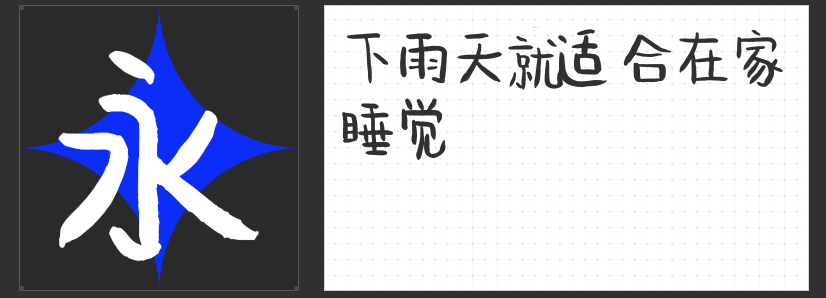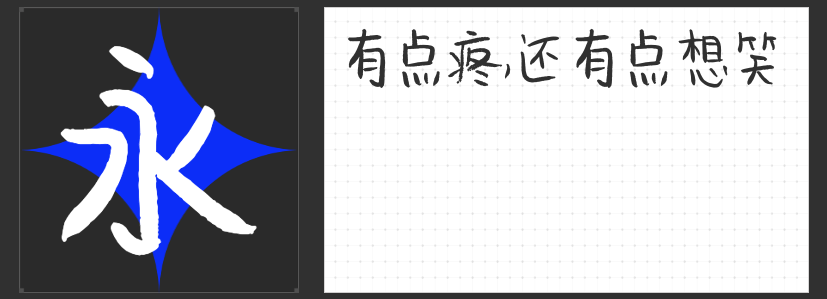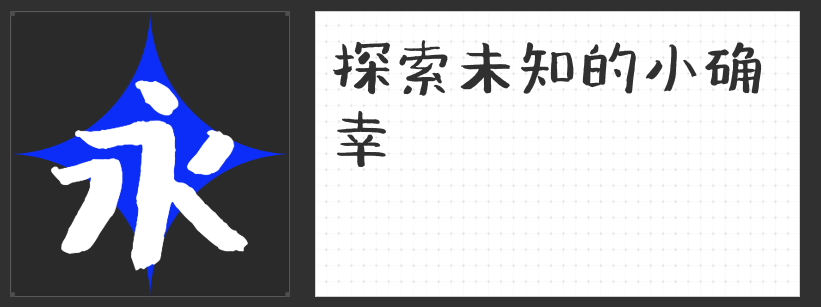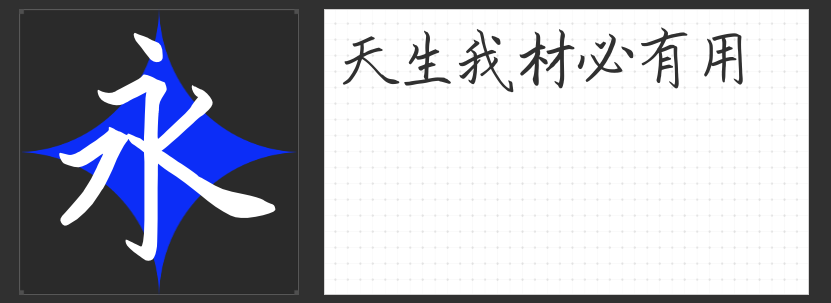
笔墨传情,手写温度——四款风格化字库字体解锁设计新维度
在数字化浪潮中,手写字体的独特韵味始终无法被替代。它承载着书写者的情感温度,传递着文字之外的视觉语言。本文精选四款风格各异的手写字库字体,它们既遵循传统书写规范,又融入现代审美巧思,为设计注入鲜活生命力。
一、安景臣标准楷书
这款字体以传统欧体为根基,却在细节处突破常规:撇捺笔画适度伸展,打破楷书常见的拘谨感,形成舒展而不失力度的视觉节奏。其字形结构严格遵循汉字书写规范,每一笔都经得起推敲,既可作为书法字帖的出版范本,亦能胜任广告标题、包装设计等商业场景。在需要传递权威感与文化底蕴的设计中,标准楷书以“正大气象”的姿态,成为平衡专业性与艺术性的理想选择。
二、高手北半川丰收体
以“顿感”为设计核心,丰收体的笔画末端自带圆润收尾,仿佛书写时笔尖与纸张的温柔触碰。这种略带笨拙的可爱感,让文字摆脱机械感,更贴近手工书写的真实温度。在需要营造轻松氛围的设计中,丰收体的微胖字形能自然软化视觉冲击,成为连接品牌与受众的情感纽带。
三、高手北半川欢喜体
将“青春”升华为设计语言:字形歪斜却充满生机,笔画粗细不均却暗藏节奏,仿佛每个字都在跳跃欢笑。这种不加修饰的稚拙感,恰恰是打破设计同质化的利器。在儿童品牌、文创产品或需要传递纯真态度的场景中,欢喜体能以最直接的方式唤醒受众的共鸣。
四、高手北半川快乐体
相较于欢喜体的随性,在保持作业本质真的同时,更注重字形的整体协调性。笔画间距均匀,结构端正却不呆板,如同学生时代被老师表扬的“模范作业”。这种“工整的灵动”使其既能胜任正文排版,亦可作为标题点缀,为设计增添一份不刻意的美好。
从规范严谨的标准楷书,到充满童趣的北半川系列,这四款字体以手写为媒介,让文字超越信息载体,成为传递情绪、塑造品牌个性的视觉符号。在追求效率的数字化时代,它们提醒我们:设计的美,往往藏在一笔一画的温度里。